Собственный шрифт для тиснения фольгой: проверка букв
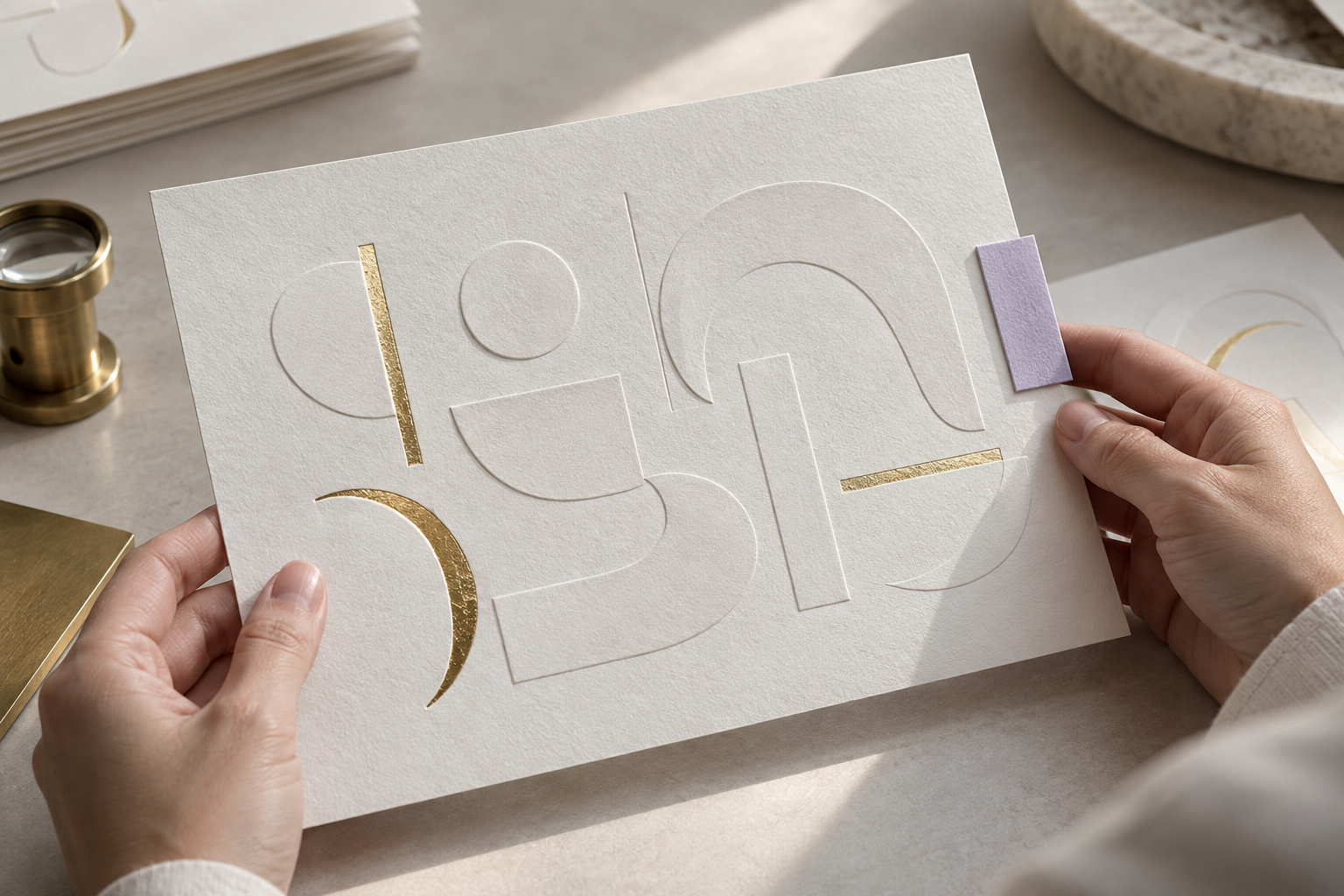
Собственный шрифт для фольги проверяют не только как файл, но прежде всего как рисунок букв в конкретных словах и размере. До передачи макета оцените просветы, тонкие штрихи, стыки и пары знаков, затем согласуйте контрольный образец с типографией: фольга и рельеф могут подчеркнуть одни особенности формы и скрыть другие. Универсальных числовых порогов для всех материалов и машин нет, поэтому ниже — практический порядок проверки без выдуманных допусков.
Здесь речь о пригодности именно нарисованного или собранного вами шрифта к фольгированию и тиснению. Подготовка слоёв, масок и файлов этикетки в целом — отдельная часть допечатной подготовки; задача этого чек-листа — выявить слабые места гарнитуры до того, как на ней построят логотип, название или короткую надпись.
Сначала определите, что именно будет тисниться
Не существует абстрактного «шрифта для фольги», который одинаково хорошо работает в любом проекте. Один и тот же набор может использоваться для короткого названия на обложке, буквенного знака, монограммы или небольшого текста на упаковке. Это разные условия чтения и разные требования к рисунку. Поэтому начните не с экспорта файла, а с описания сценария: какие слова попадут под отделку, где они будут стоять, на каком материале и будет ли фольга плоской или сочетаться с рельефом.
Запишите, какие знаки в реальном тексте повторяются чаще всего, где окажутся самые плотные сочетания и какие буквы или символы нельзя потерять. Для логотипа это может быть одна необычная пара, а для серии названий — несколько десятков разных сочетаний. Проверьте именно предполагаемые строки: тест на слове «МИР» ничего не говорит о буквах и стыках в названии «МОЛОКО».
- Зафиксируйте короткие строки, которые действительно будут выполнены фольгой или рельефом.
- Уточните у производства материал, способ отделки и формат контрольного образца.
- Отметьте обязательные буквы, цифры, знаки препинания и версии кириллицы или латиницы.
- Решите, должна ли надпись оставаться читаемой с расстояния или работать как крупный знак.
Проверьте просветы и внутренние формы
Первое уязвимое место — внутреннее пространство знака, или просвет. В «О», «Р», «В», «А», «Ф» и других буквах оно может быть замкнутым, узким или открытым. Если участок слишком тесен для выбранного размера и материала, блестящая поверхность способна визуально сократить его; в рельефе края могут выглядеть тяжелее, чем на плоском экранном изображении. Важно сравнивать не только общую площадь просвета, но и его форму: острие, узкая шейка или очень тонкий мостик часто становятся первым местом, где знак теряет ясность.
Распечатайте или выведите формы в масштабе будущего изделия и рассматривайте их без увеличения экрана. Отдельно проверьте маленькие контрформы, места схождения штрихов и те просветы, которые заметны только при внимательном рассматривании в векторном редакторе. Для необычного фирменного знака полезно подготовить несколько вариантов буквы: более открытый, более простой и исходный. Тогда разговор с технологом будет предметным, а не сведётся к просьбе «сделать чуть тоньше».
Сравните толщины штрихов и тонкие детали
Контраст между основным и тонким штрихом придаёт шрифту характер, но чрезмерно деликатная деталь может исчезнуть или выглядеть непоследовательно после отделки. Проверьте засечки, острые окончания, диагонали, соединения и места, где тонкая линия переходит в плотный участок. У рукописного рисунка внимательно посмотрите на имитацию пера, петли и перекрывающиеся штрихи; у геометрического гротеска — на тонкие горизонтали и острые внутренние углы.
Не утолщайте все элементы автоматически. Если механически расширить контуры, можно закрыть просветы, изменить пропорции и уничтожить замысел начертания. Сначала определите, какие элементы критичны для узнаваемости. Затем сделайте альтернативный оптический вариант: упростите только уязвимую деталь, смягчите слишком острый стык или увеличьте внутреннее пространство. Сравните обе версии в рабочем размере и попросите типографию оценить их на выбранном материале.
Приёмка зависит не от одного кегля или значения толщины. На результат влияют конкретный способ отделки, материал, форма букв, площадь и соседство крупных сплошных зон. Производитель фольги Foilco отдельно обращает внимание на риск заполнения мелких деталей и на размер контрформ; типография Boxcar Press отмечает, что фольгированные буквы могут казаться визуально плотнее, а тонкие выворотки — закрываться. Эти наблюдения объясняют, почему экранный макет не заменяет проверку на реальном носителе.
Оцените интервалы и соседство букв
В готовом шрифте кернинг на экране может выглядеть аккуратно, но отделка меняет оптический баланс строки. Узкий промежуток между двумя буквами способен стать едва различимым, особенно если рядом находятся диагональ и вертикаль, пара округлых форм или нависающая засечка. Пройдите все рабочие сочетания, не ограничиваясь стандартными тестовыми парами: имя бренда, фамилия, короткий слоган, цифры в номере серии.